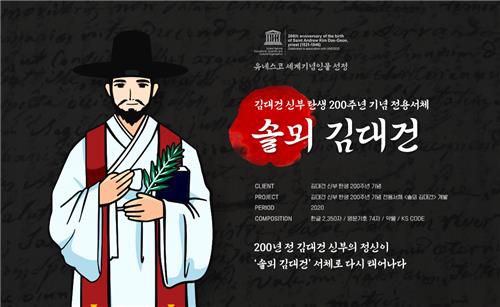
솔뫼 김대건체 |
(당진=연합뉴스) 이은파 기자 = 충남 당진시는 대한민국 최초의 사제인 김대건(1821∼1846년) 신부 탄생 200주년과 유네스코 세계기념인물 선정 1주년(11월 14일)을 기념해 그의 폰트와 웹툰을 개발, 배포한다고 13일 밝혔다.
이 사업은 당진시가 지난 7월 충남정보문화산업진흥원과 김대건 폰트 및 웹툰 개발, 동화책 편찬, 홍보 사이트 구축 등을 골자로 한 업무협약을 체결한 데 따라 추진됐다.
김대건 신부 폰트로 제작된 '솔뫼김대건체'는 김대건 신부 서한 필사본을 기초로 한글 자소의 형태를 분석하고 모양새별로 재분류해 글씨의 특징을 추출했다.
세로쓰기로 쓰인 붓글씨를 현대 조판 환경에 맞게 가로쓰기 형식으로 변경하고, 여러 환경에 적합하도록 가독성에 중점을 두어 정돈했으며, 현대적 재해석을 통해 김대건 신부의 시대정신을 알리기 위해 개발했다고 시는 설명했다.
개발에는 주관기관인 써밋디자인과 디자인210이 참여했다.